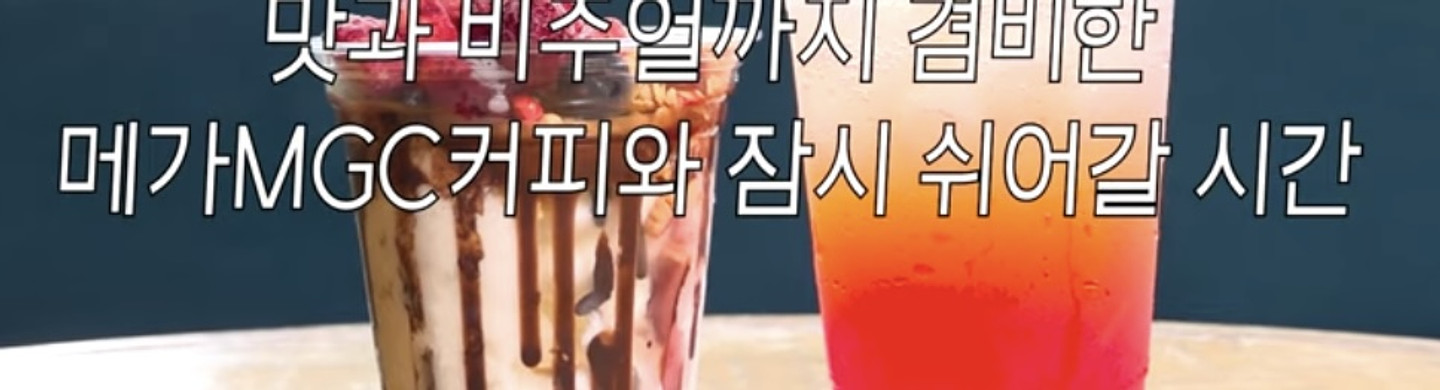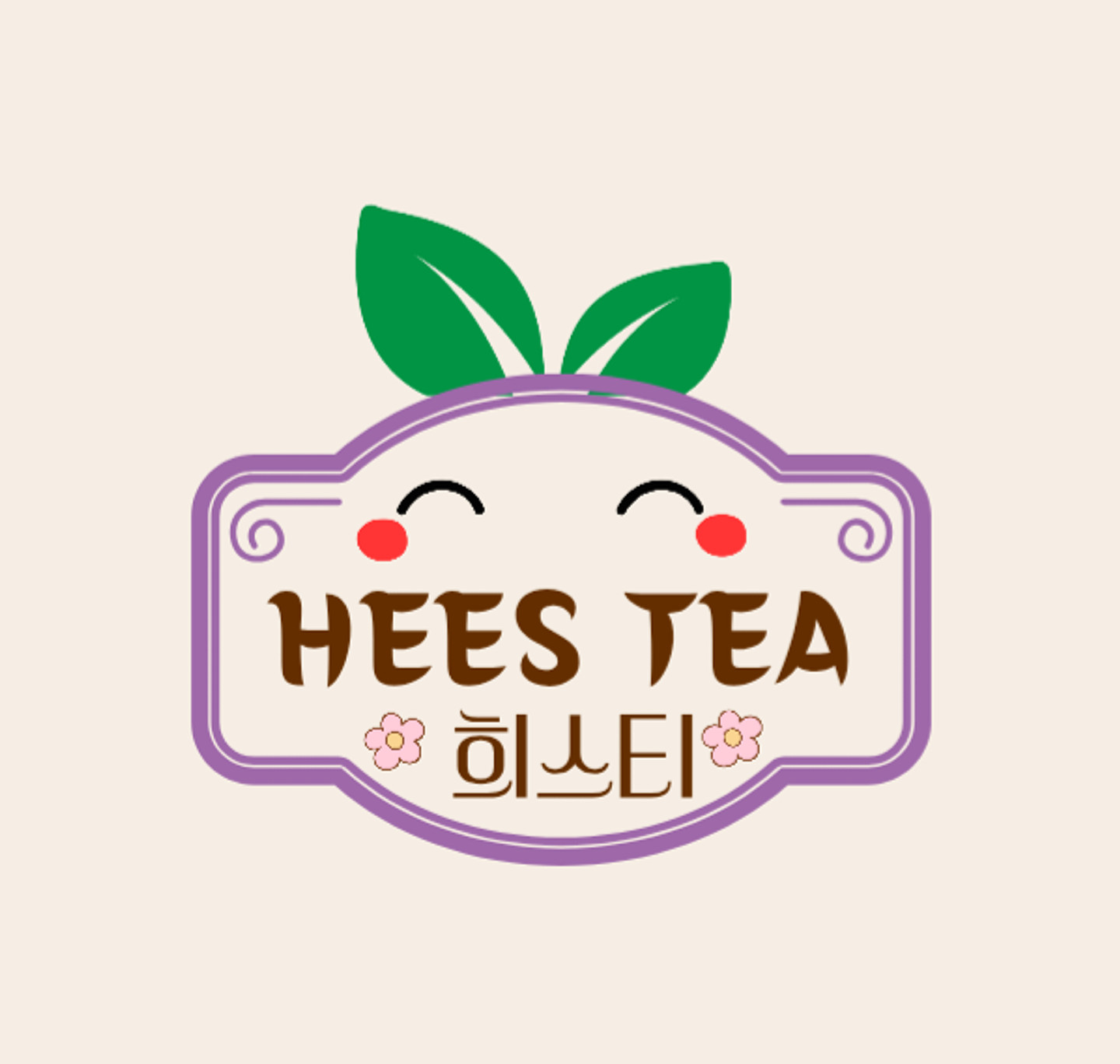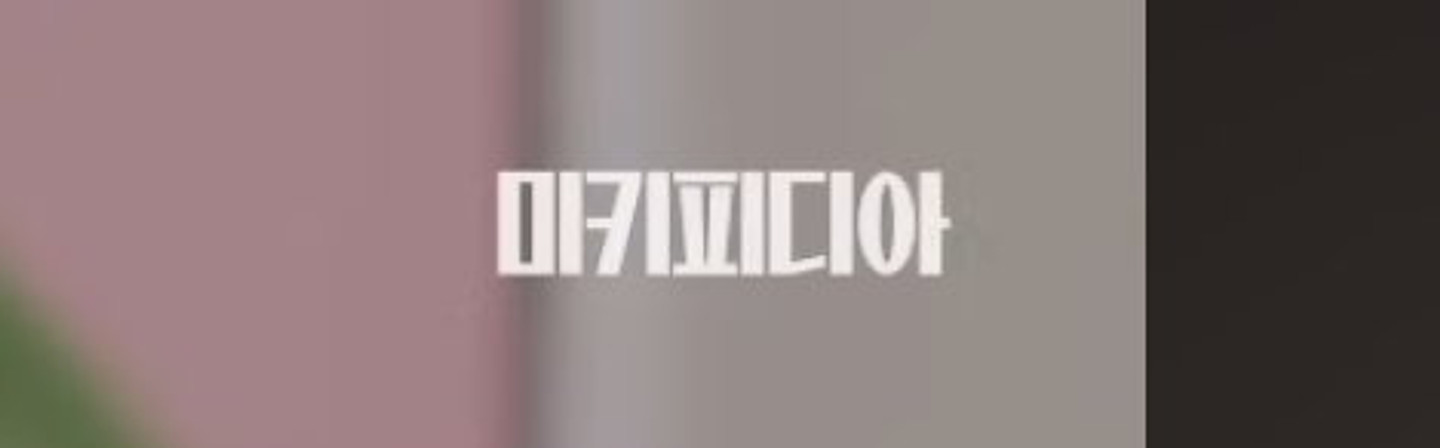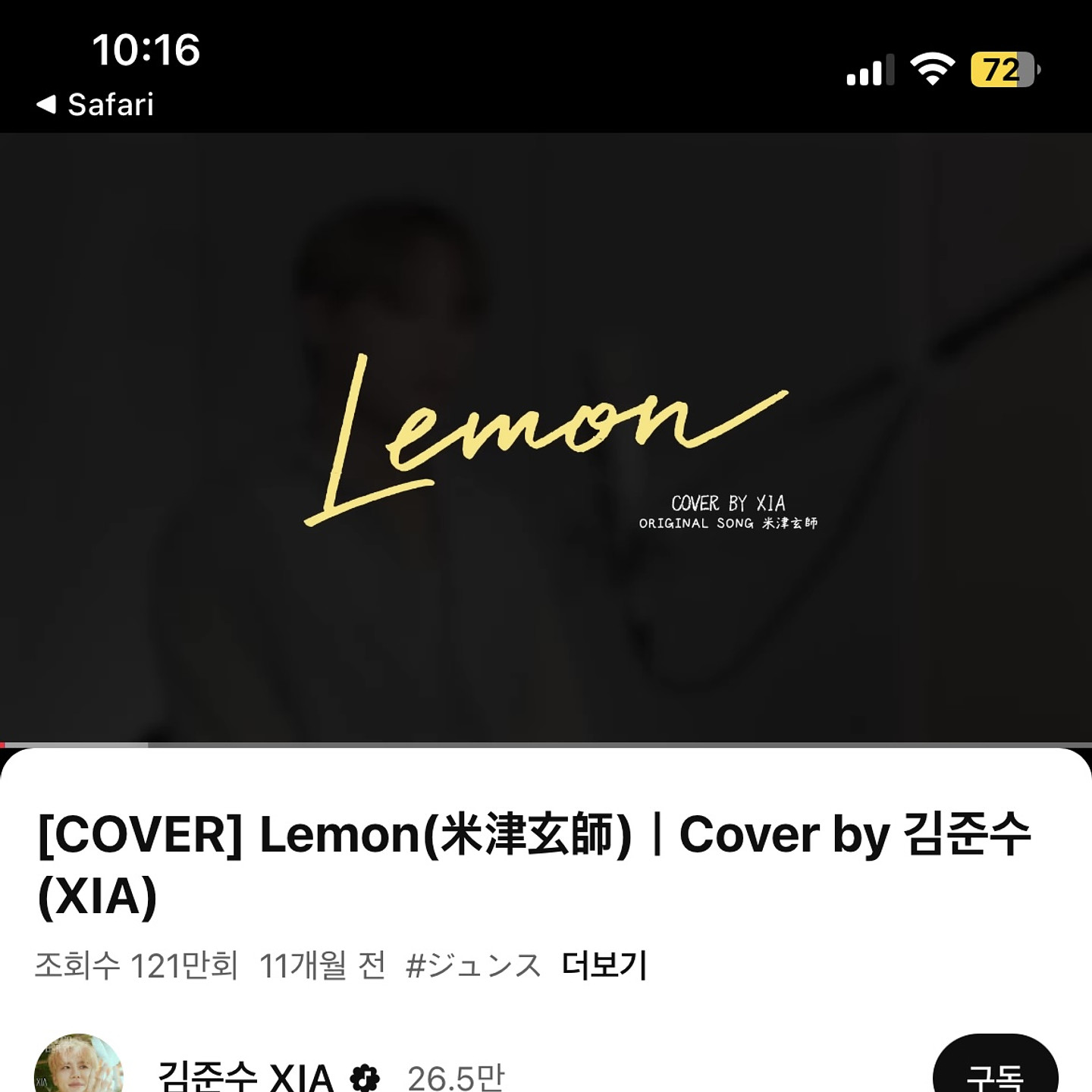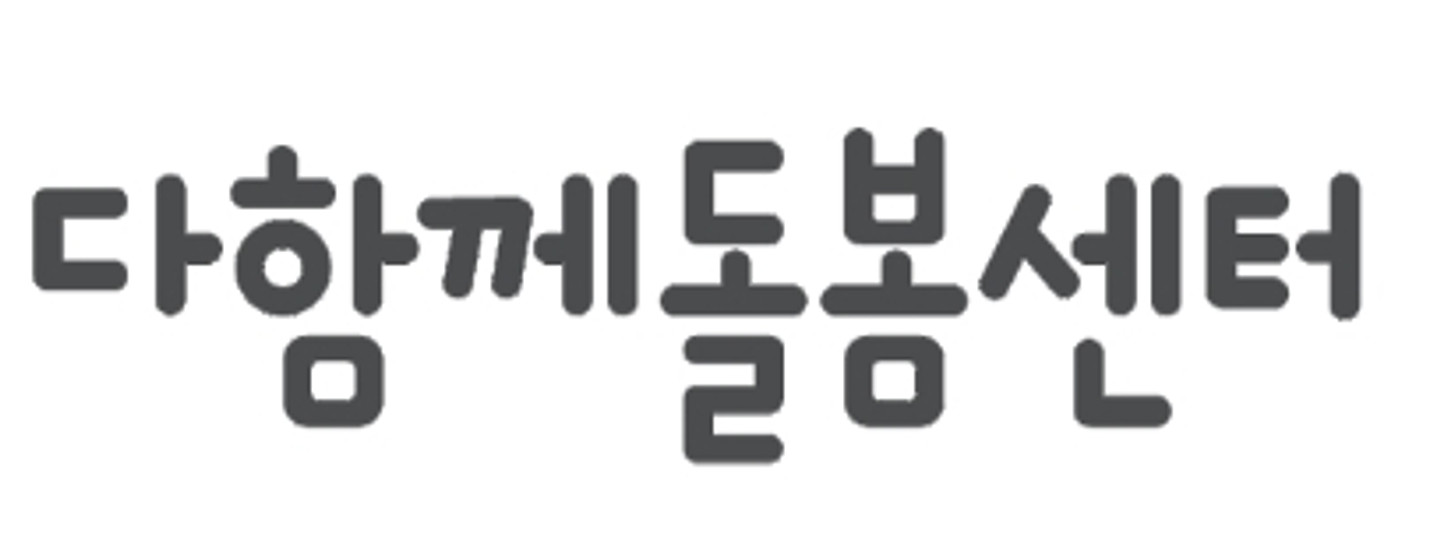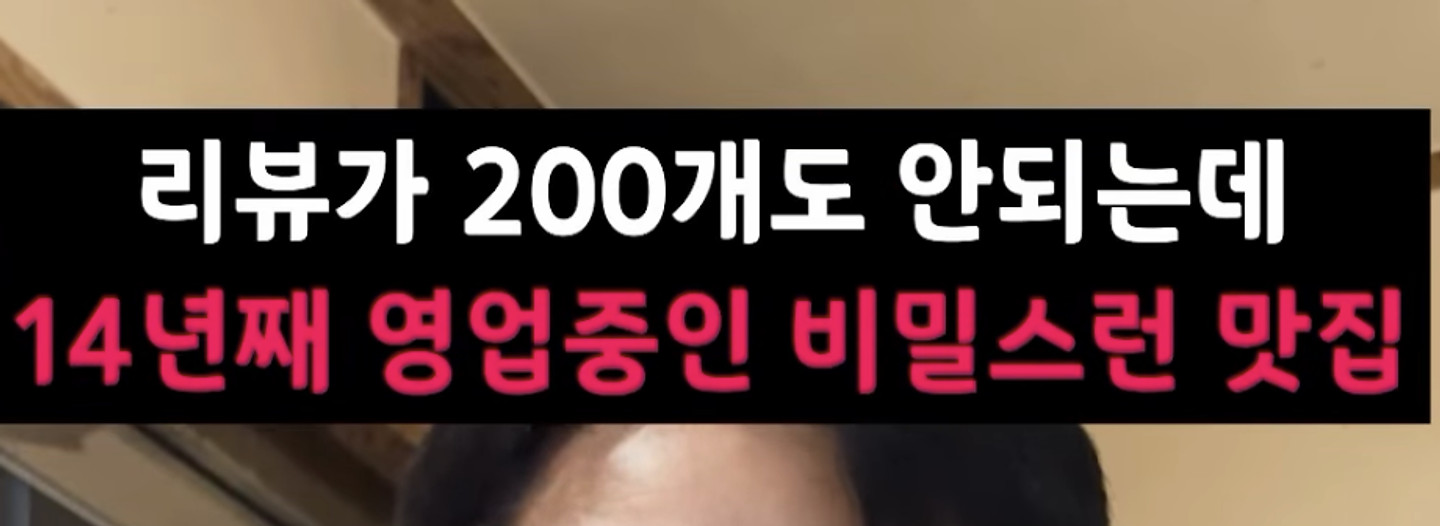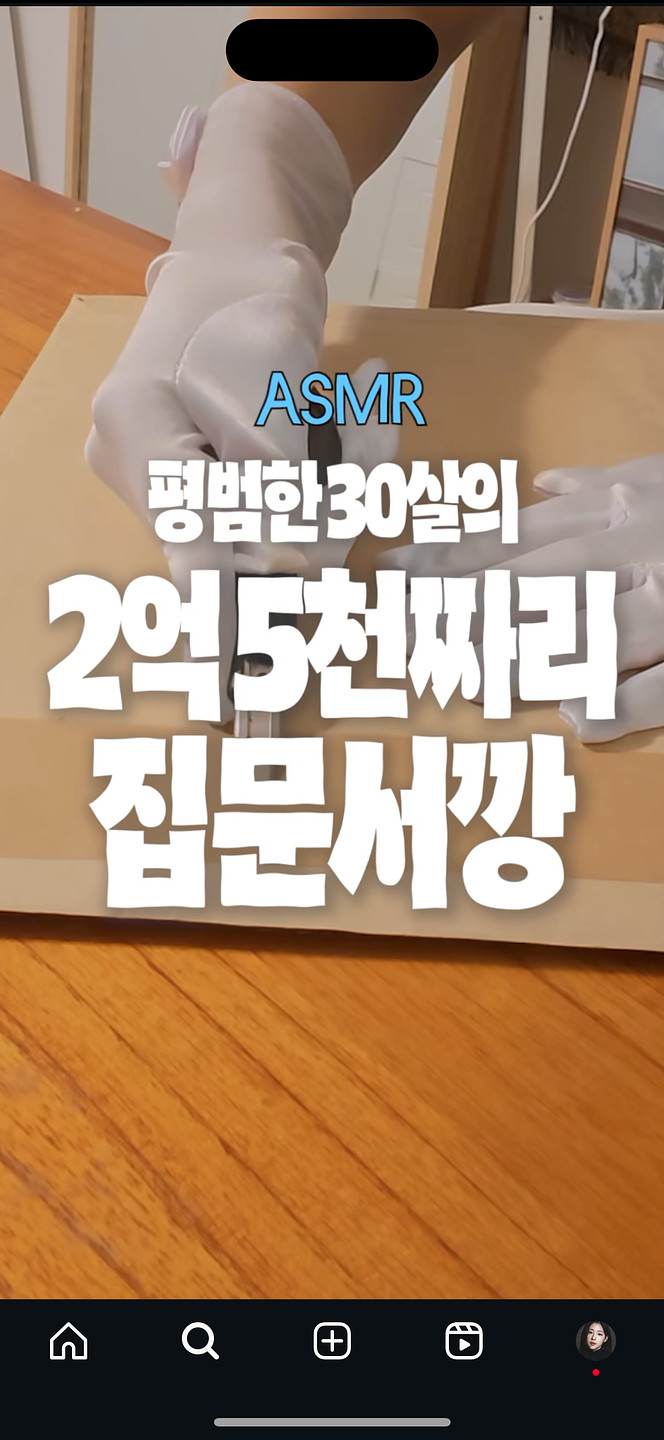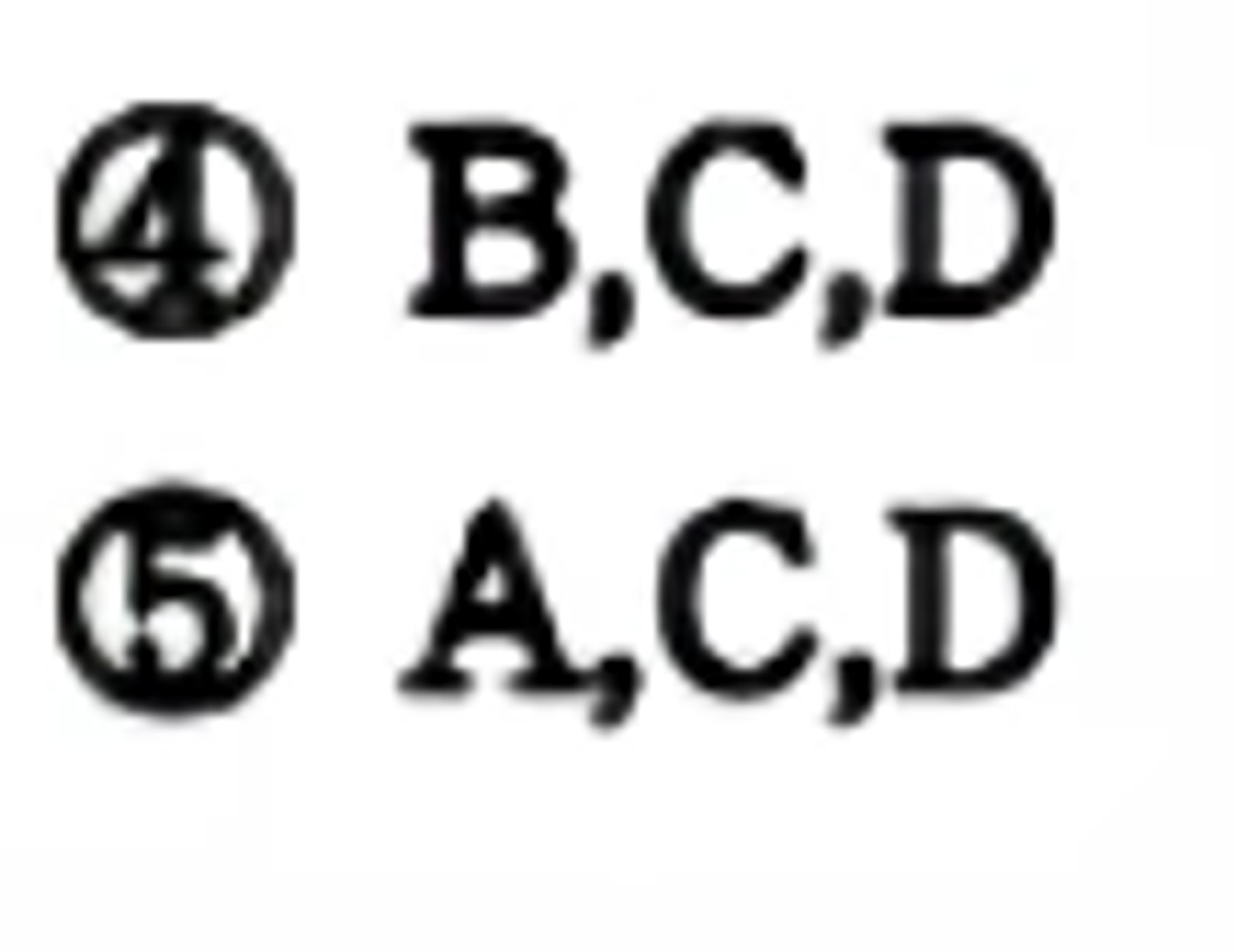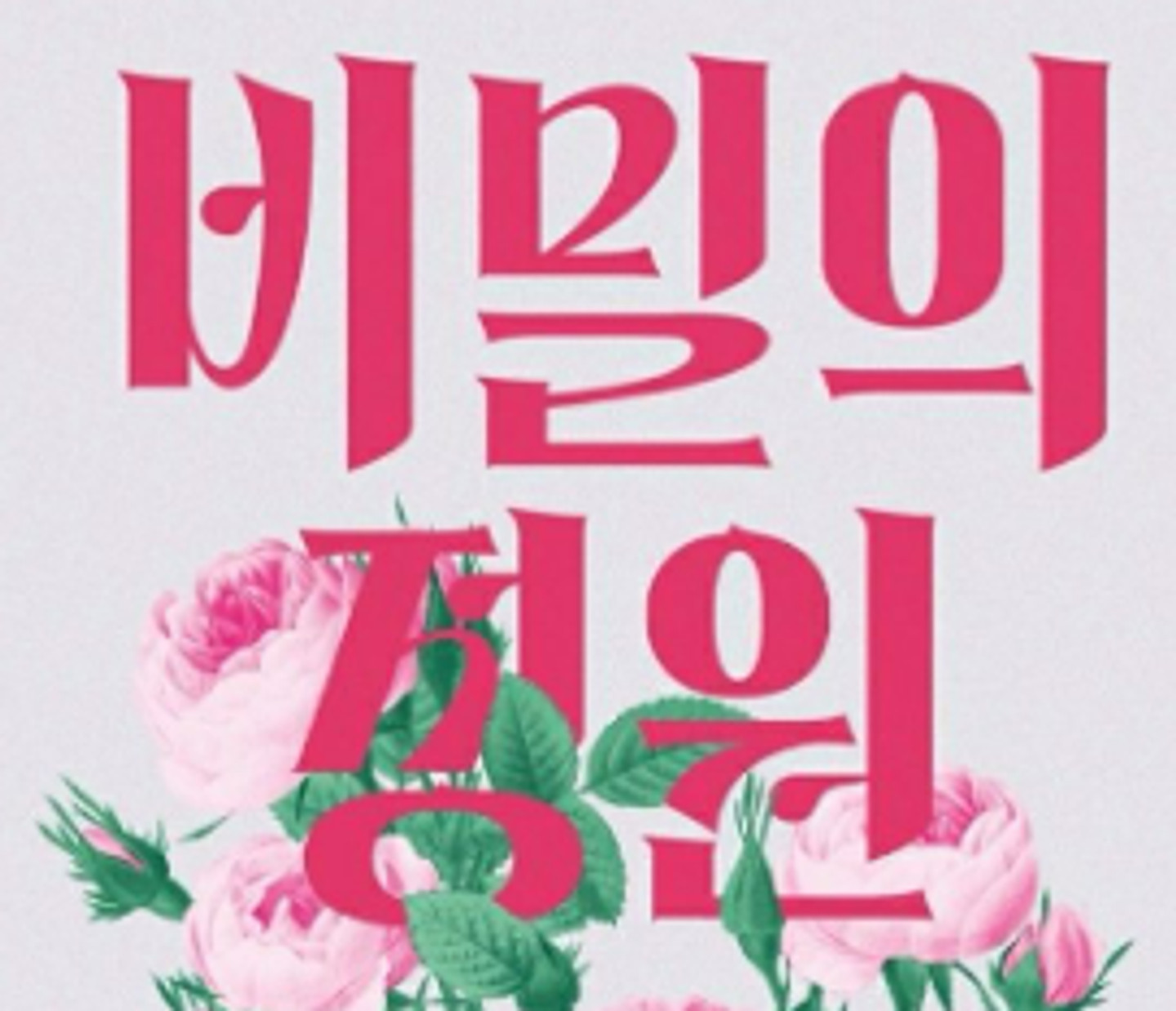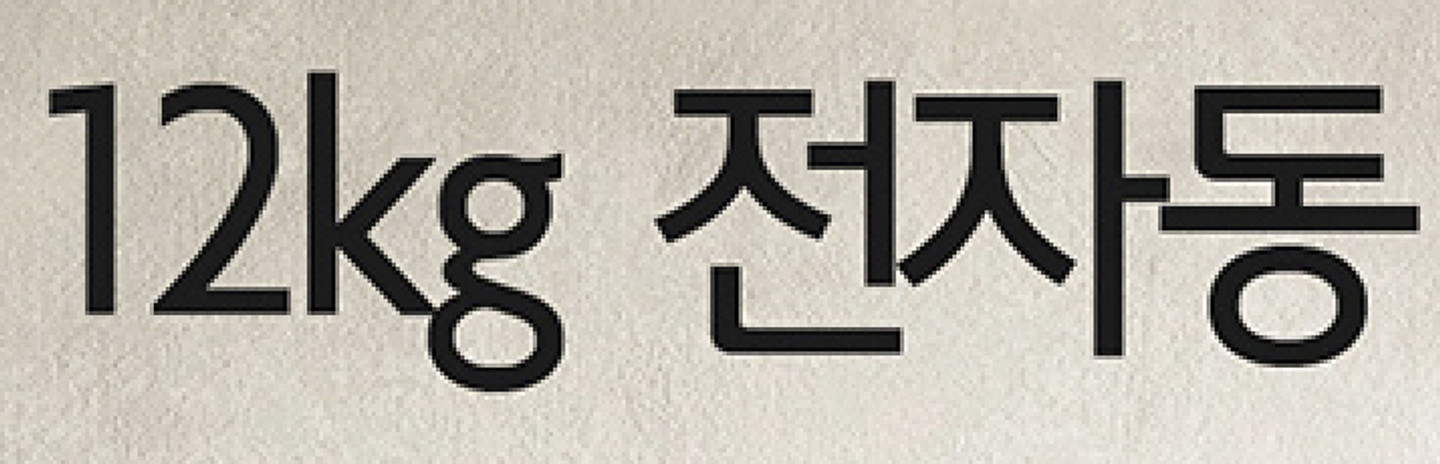
이 폰트가 궁금합니다
폰트좀 알려주세용용ㅇ
놀토 놀라운토요일 자막이에요 무슨 폰트인지 궁금합니다 ㅠㅠ
이거 무슨 폰트일까욤...
로블록스 한국 끝말잇기 인게임입니다.
이런 폰트 있을까요?ㅠㅠ
드라마 '그해 우리는' 제목 폰트가 궁금해요. 최대한 비슷한 폰트 알려주시면 정말 감사하겠습니다.
이 폰트가 뭘까요?
이 폰트 아시는 분?
이거 밑에 자막 뭘까요 폰트 ㅠㅠ 코르티스 자컨입니다
옆으로 납작하게 눌린 폰트 알고 싶어요
안녕하세욤 이 폰트가 뭔지 알 수 있을까요? 일러 파일을 받았는데 아웃라인 어쩌구해서 폰트가 확인이 안되네요 ㅠ 동일하게 써야하는데,,,, 흑흑 + 어머나!!! 답글 다는 기능을 못찾아서 글 수정해요!! 이걸 어떻게 찾으신거죠?! 정말 감사합니당 ><!!!!! 계신 방향으로 절 올리구 잘게요 ㅎㅎ!!!!!!
무슨 폰트인지 알려주세요 ㅠㅠㅠ
이 폰트도 무슨 폰트인지 알려주시면 감사하겠습니다ㅜㅜ 항상 답변 달아주시는 분들께 감사하며 사랑합니다 ♡♡
폰트가 궁금합니다
뭐랄까 연필로 쓴듯한 폰트입니다
폰트좀 알려주세용
동경닭강정 폰트 뭘까요??ㅜㅜ
두근두근 비밀 업로드 대작전 폰트가 궁금합니다
글씨체
무슨 글씨체인가요?
무슨 폰트인지 아시는 분 계신가요?ㅠ
이 글씨체 뭘까요?ㅠㅠ
이거는 뭘까요
짜잔씨 폰트 제발요ㅠ (조선굴림 절대 아니니까 답변하지 마세요 ㅠㅠㅠㅠㅠㅠ)
무슨 폰트인가요… 설정 잘 못 건드렸더니 날라갔어요… Ba로 시작했던 것 같아요
무슨 폰트인지 아시는분 있으신가요
이 폰트 궁금해요 ㅠㅠ
폰트명
무슨 폰튼가요?
폰트 뭔지 알 수 있을까요?
저 파란색 글씨 서체가 뭔가요?
안녕하세요 지피티가 만들어준 글씨체인데 이런 글씨체 혹시 존재할까요~?
네온 작업된 서체인데 비슷한 서체도 추천부탁드립니다
이 폰트 무엇인가요?
어떤 폰트일까요? 궁금해요 !!
유튜브에서 봤어요
국보온돌침대 폰트 기존 있는 폰트인가요? 기존 있는 폰트를 본거 같기도 하고.. 고수님들 알려주세요
무슨 폰트인가용
그 제작자의 손글씨잉가 했는데 종종 본 것 같어서요 뭘까요?
요거 어떤 폰트 인지 아시는 붐
뭔가 어린아이 폰트?? 이런 느낌의 이름이였던 걸로 기억하는데... 제발 알려주세요!ㅜㅜ
이 폰트 뭐에여 인스타에서 검색할때 가끔 뜨던데 ㅠ
폰트명이 궁금해요.
사진속 기사 폰트가 뭘까요?
안녕하세요! 이 폰트가 무엇인지 아시는 분 계실까요?
위에 굵은 폰트와 아래 작은 폰트 뭘까요?
이 폰트 정보가 뭔가요?
이 폰트 뭘까요? ㅜㅜ